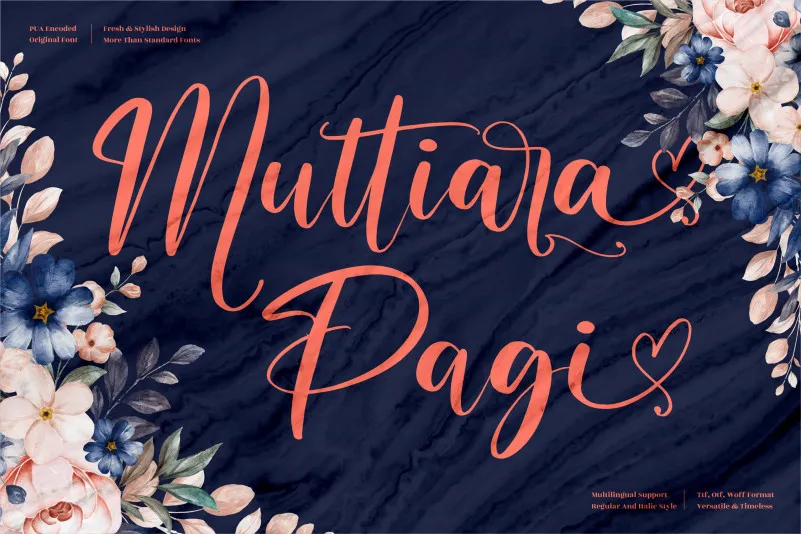
Muttiara Pagi Font – Download Grátis
A Muttiara Pagi é uma elegante tipografia com traços suaves que se destaca em qualquer projeto, seja para logotipos ou projetos de marca, mobílias e embalagens de produtos, até mesmo para camisetas, livros, cartões de nome, convites de aniversário, etiquetas, fotografias, água-marinhas e eventos especiais. Com seu charme romântico, a Muttiara Pagi oferece um toque especial e sofisticado que torna qualquer projeto único e envolvente. Ideal para uma variedade de aplicativos, como cartões de visita, capas de livros, selos para presentes, etiquetas para pratos ou copos, ou até mesmo para adicionar um toque delicado a suas fotografias ou criações digitais. Através dessa fonte sofisticada e romântica, você pode criar designs que exalam beleza e charme. É perfeita tanto para uso em papel quanto digital, permitindo uma personalização única e inspiradora. Seja um designer gráfico, profissional de branding ou simplesmente alguém que aprecia uma boa fonte para seus projetos, a Muttiara Pagi é uma escolha excepcional.